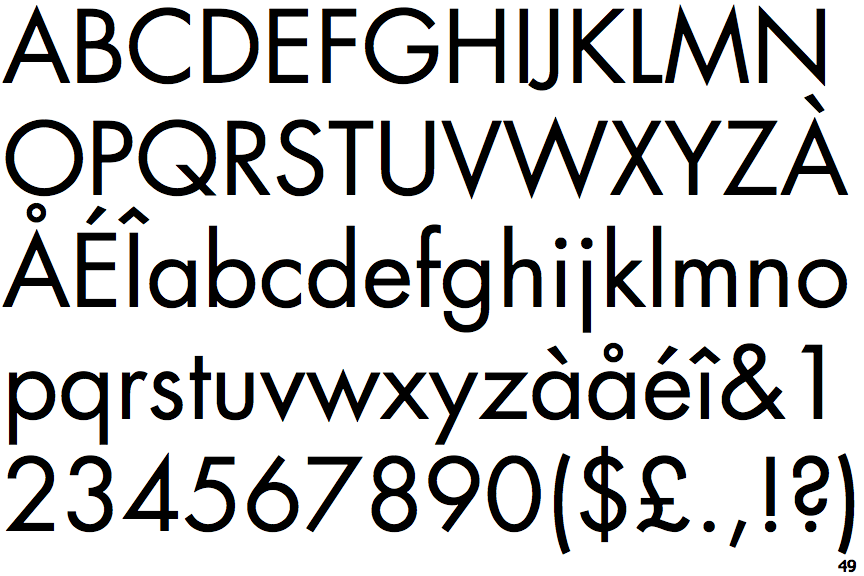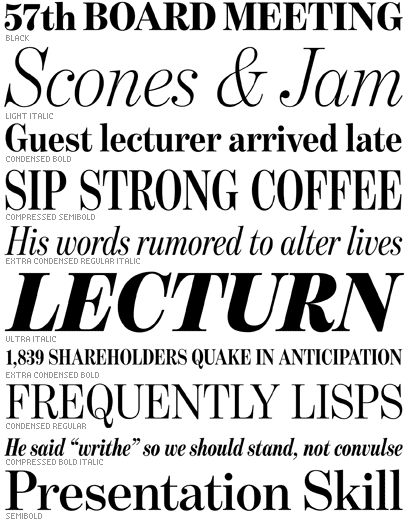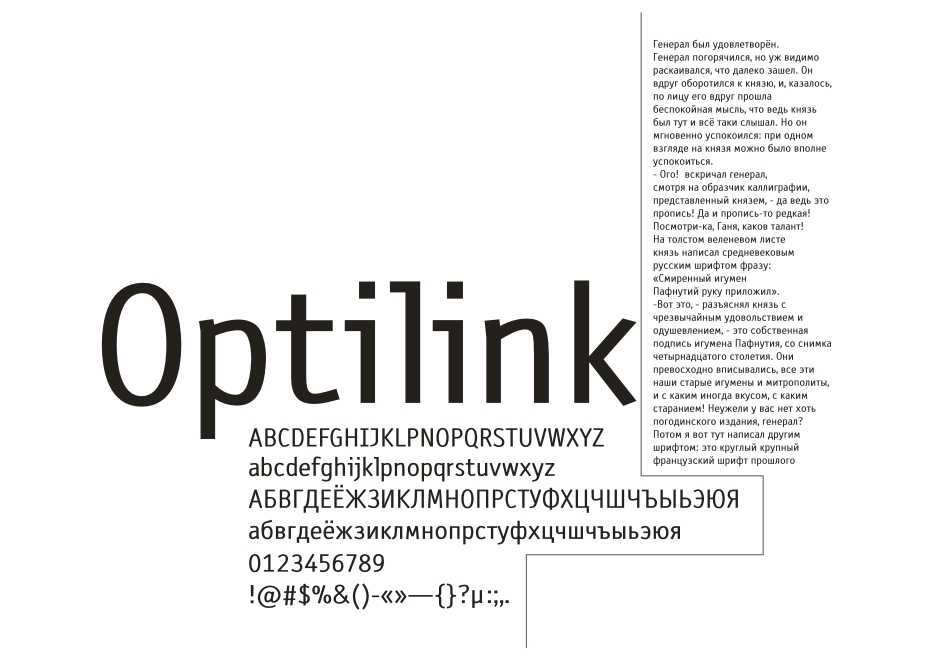
Тренды шрифтов для сайта в 2023 году. Как выбрать и можно ли использовать стиль леттеринг?
Шрифт — это буквально почерк вашего бизнеса, важный визуальный элемент для создания правильного восприятия вашего бренда. Текст зачастую выступает главным способом коммуникации компании с клиентом. Использование гармоничных сочетаний шрифтов на сайте, в рекламных материалах и других составляющих айдентики помогает сформировать образ компании, отражающий ее позиционирование.
То, какой шрифт используется в веб-дизайне, косвенным образом влияет и на конверсию: посетители интернет-портала более лояльны к контенту, представленному читабельными — чёткими и различимыми шрифтами, в этом случае они с большей вероятностью станут постоянными клиентами.
Рассмотрим, каков же самый лучший шрифт для сайта и логотипа и какими могут быть критерии выбора подходящего шрифта, а также чем хорош стиль леттеринг и в каких случаях применим.
Популярные шрифты 2023 года
В трендах 2023 шрифты с засечками, ультратонкие линии, «сплющенные» буквы, контролируемый хаос, упрощение и минимализм, градиенты, надписи «от руки» и отсылки к ретро, брутализм, экспериментальные и сугубо декоративные шрифты, азиатская тематика, игры с объемом и формой.
Шрифты с засечками
Вносят настроение доцифровой эпохи: Recoleta, Voga, Magfirah, Selvina. Элегантные, декоративные, с налетом ретро, и особенно настроения ар-деко. Раньше их чаще всего можно было встретить в глянцевых журналах, презентациях, открытках, принтах. Теперь шрифты с засечками вновь завоевывают глобальное визуальное пространство в самых разных сферах.
Минимализм и современность
Подобным шрифтам присуща лёгкость, динамика, оригинальность, лаконичность, использование геометрических элементов в умеренном количестве. Это, к примеру: Codec Pro, Impossible, Nevrada, Cremona, Sofia Font, Black rovers Font, Agnostic Font, QSansPro, Mofita, Munich Sans.
Стремление к минимализму и лаконичности во всем от шрифтов до иллюстраций — это один из устойчивых трендов последних 5–10 лет. В 2023 одной из его «граней» станет использование ультратонких (и вытянутых вверх) шрифтов. Особенно эффектно они смотрятся в серой гамме, вызывая ассоциации с карандашным наброском.
Нередко дополняются градиентным фоном, что с одной стороны, компенсирует лаконичность и строгость логотипа, а с другой — отдает дань другой визуальной тенденции (градиенты — см. обзор популярных трендов в вебе).
Контртренд, в рамках того же минимализма — это, напротив, использование массивных акцентированных шрифтов (без засечек), максимально растянутых по ширине — своеобразный эффект «приплюснутого» текста (как в шрифтах Neutro и Vlaenella Bold). Впрочем, и тонкий шрифт также может быть растянут.
Еще один популярный прием, который часто используется одновременно с массивными буквами — это контурная типографика без заливки, то есть у отдельных букв или слов обозначен лишь контур. Это особенно удобно как способ расстановки визуальных акцентов — не меняя шрифта, можно визуально выделить отдельные моменты текстового послания.
Кроме того наблюдается массовая тенденция к упрощению/стилизации логотипов компаний. Это проявляется в том, что, а) международные бренды все чаще выбирают простой черный цвет, вместо яркости, б) упрощают или вовсе убирают из логотипа все графические элементы, оставляя одно лишь только шрифтовое название.
Одна из лучших иллюстраций озвученных тенденций — логотип BBC, за него в 2021 году компания заплатила 1,8 млн долл., что делает его одним из самых дорогих логотипов в мире. По сути это просто три белые буквы, расположенные в трех черных квадратах. И — в инверсивном варианте — наоборот.
Ретро стили
Всегда актуальны, создают налёт лёгкой ностальгии, романтики. В то же время могут подчеркивать немейнстримовый характер компании, проверенное временем качество или апеллировать к определенной временной эпохе, ее ценностям и настроению.
-
На пике популярности декоративная графика в духе конца XIX — начала XX века, когда дизайнеры отвергали стандартизацию и единообразие промышленной революции.
-
«Новой» классикой современности считается стилистика ар-деко с ее нарочитой декоративностью, орнаментальными мотивами, характерными шрифтами и геометрическими формами.
-
Минималистичная эстетика 70-х также в духе времени — стильные шрифты «старой школы», спокойная теплая цветовая палитра с мягкими тенями. Особенно актуально для упаковки и оформления больших объемов текстового контента.
-
Приходит мода на 90-е и 00-е, что находит отражение и в шрифтах. Так, эстетика 90-х диктует моду на яркие цветовые палитры, металлические оттенки, зернистые текстуры, некоторую брутальность. 00-е характеризуются неоновыми цветами, яркими бликами а-ля CD диск, технологичностью и футуристичными фантазиями.
Вечный» долгоиграющий тренд — романтика 60-х (толстые плавные изгибы букв, характерные для кино-постеров и пластинок тех времен — примеры: Aesthetic, Curious Type, Big Bro, Groovy, The Banthink). Примеры: Miami Vice, Alba, Nasalization, Rotola TH Pro, Liberta TA, 8th Avenue, 6th Aniversario.